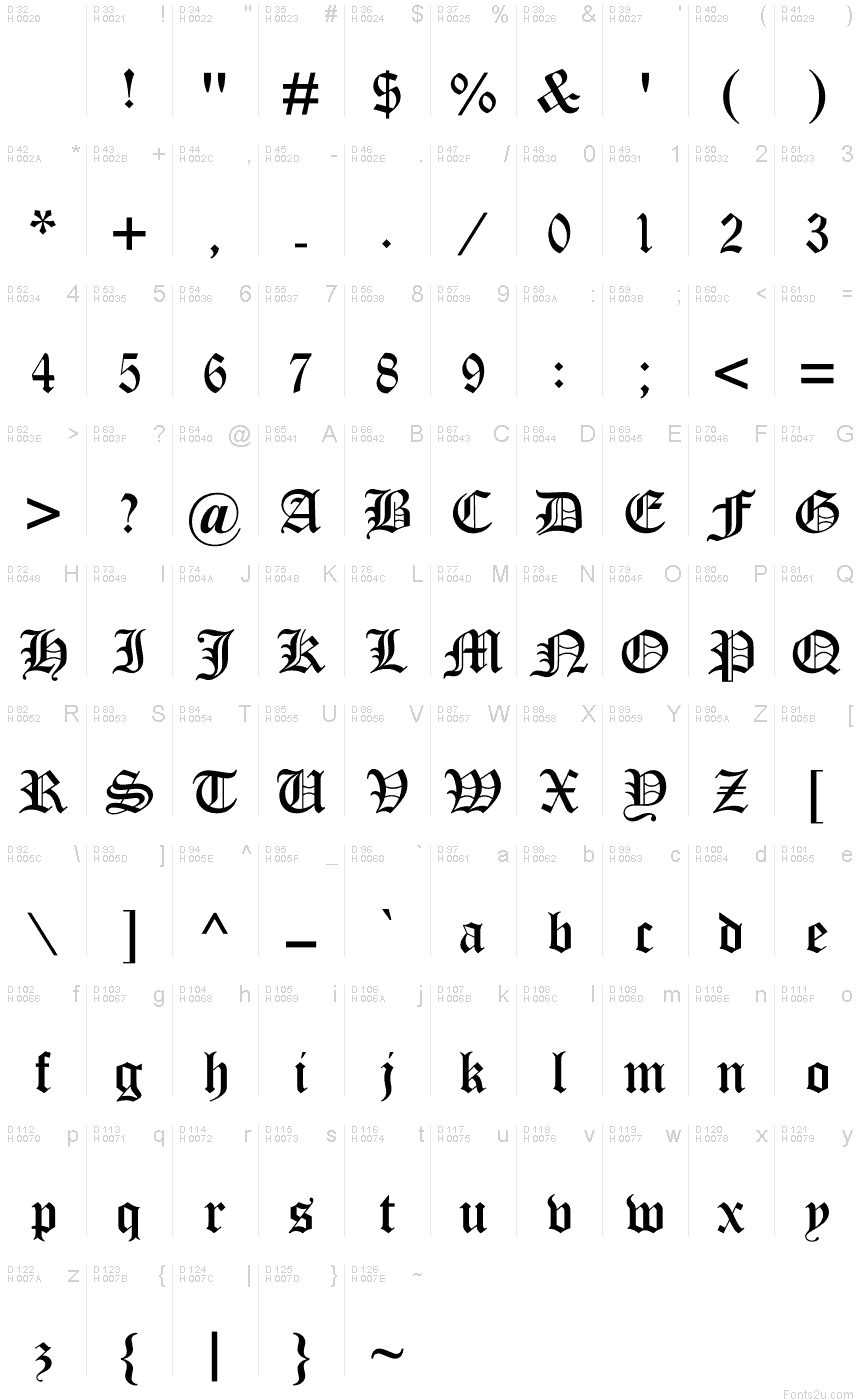
UKIJ Kufi Tar od Uyghur Computer Science Association to darmowy, ozdobny font typu blackletter o formalnym, starodawnym charakterze. Litery wyróżniają się ostrymi, łamanymi krzywiznami, ciernistymi łączeniami oraz szerokimi, wstęgowymi pociągnięciami, które nadają krojowi heraldyczny, kaligraficzny rytm, wykraczający poza zwykłą geometrię.
Krój ten doskonale sprawdzi się w brandingu kawiarni, etykietach barowych, plakatach muzycznych, okładkach książek, ulotkach i kartach tytułowych, gdzie średniowieczny lub ceremonialny klimat wzmacnia przekaz. Jako darmowy font, świetnie radzi sobie również w monogramach, krótkich nagłówkach i inicjałach, ponieważ gęsta faktura i wyraziste sylwetki liter robią znacznie większe wrażenie niż neutralny krój.